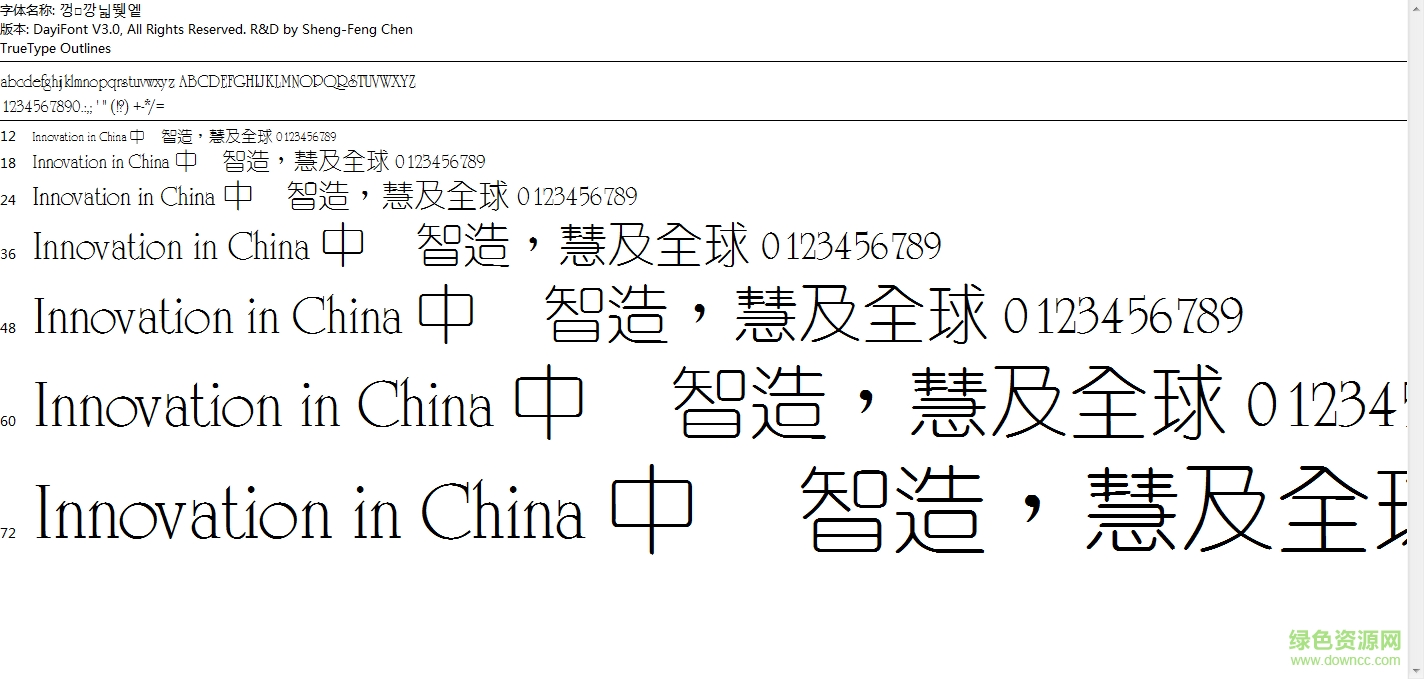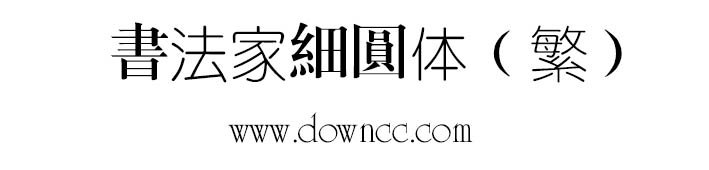
書法家細圓體是一款簡潔大氣的Windows字體,可直接導入到電腦中,字型大小均勻,偏細一些,支持漢字、數(shù)字、英語三種文字轉(zhuǎn)換功能,應(yīng)用范圍非常廣泛,歡迎來綠色資源網(wǎng)下載使用!
書法家細圓體給人以優(yōu)美端莊的姿態(tài),繁體字的特性加上細圓字體的結(jié)合讓人越看越喜歡。